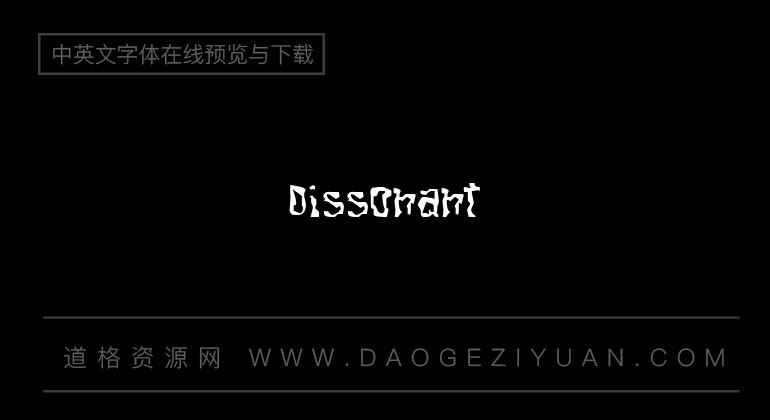
Dissonant 是一款字体,它具有杂乱的外观,表达出强烈的激情和情感。它的字体风格灵感来自20世纪的流行文化,以及被称为“艺术家的实验室”的新艺术运动。它的字体设计灵感来自于艺术家们对艺术和表达的探索,以及他们对材料,形状,线条和文字的探索。它的字体设计具有抽象的风格,具有独特的外观,能够表达出独特的情感和情绪。它的字体设计适合用于各种类型的设计,如海报,标识,商标,报纸,杂志和网页等。内容介绍
Dissonant是一款非常不错的手写艺术字体,具有很好的视觉感,适合于文化类的宣传设计、商业类品牌的广告和产品包装设计以及个性化文字排版等较多场景。